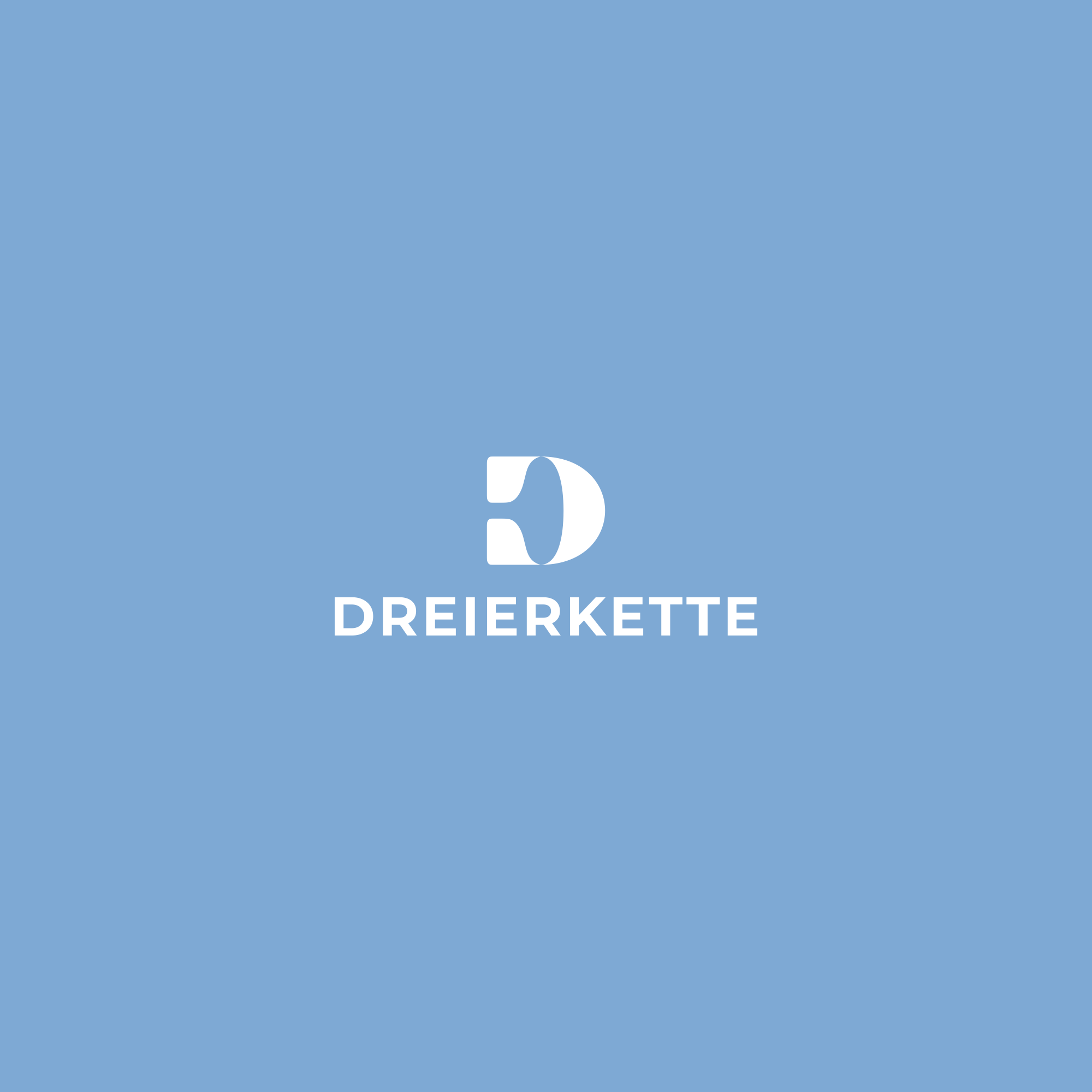
Logoschrift "Dreierkette" gesucht!
ich habe dieses fertige Logo bekommen und soll herausfinden welche Schrift für den Firmennamen "Dreierkette" verwendet wurde.
Damit wir weitere Drucksorten mit diesem Font für das Unternehmen gestalten können.
Tippe auch aufgrund des D, was in meinen Augen etwas zu breit geraten ist, auf die Montserrat.